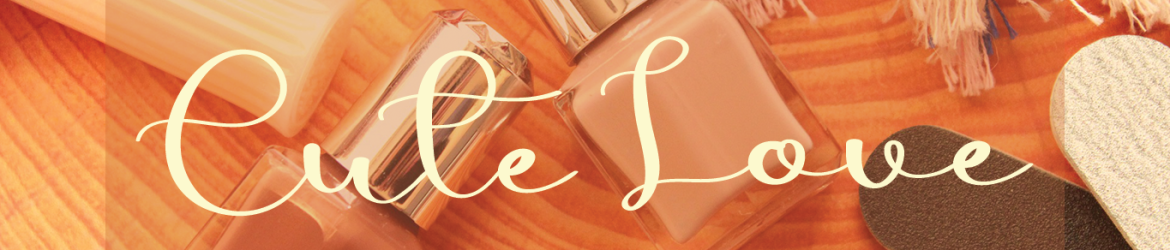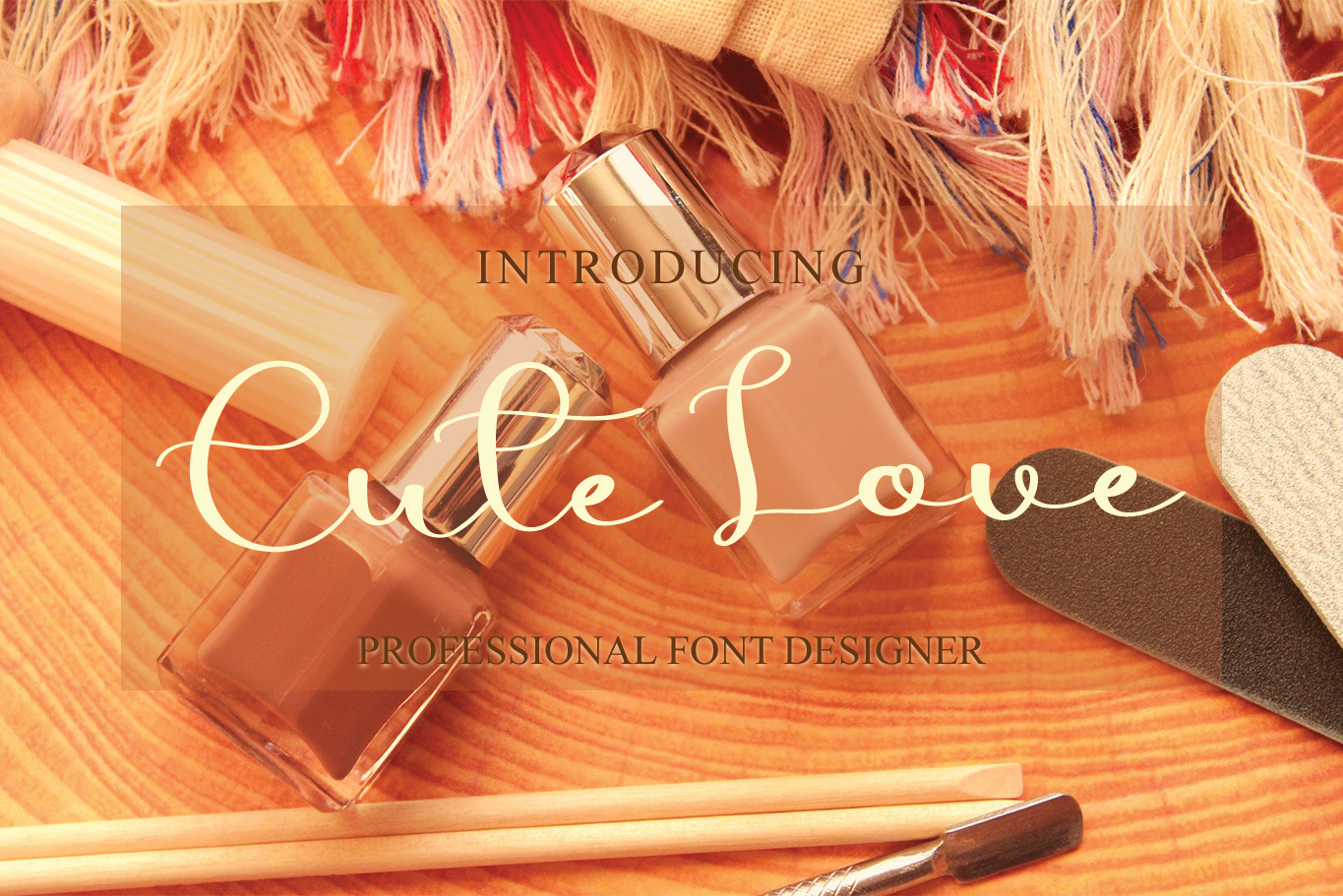
Cute Love Font
A ‘Cute Love Font’ é uma elegante e refinada tipografia script que transmite sofisticação e esplendor. Esta fonte chic possui alternativas estilizadas e ligaturas criativas, tornando-a perfeita para qualquer projeto. Perfeito para aqueles que buscam uma fonte suave para cartões de aniversário, gráficos de amor ou até mesmo para mensagens pessoais, esta elegante fonte se destaca como um recurso indispensável para designers e criativos. Com sua abordagem delicada e sofisticada, a ‘Cute Love Font’ é uma escolha perfeita para criar algo único que expressa afeto de maneira envolventemente romântica e natural.